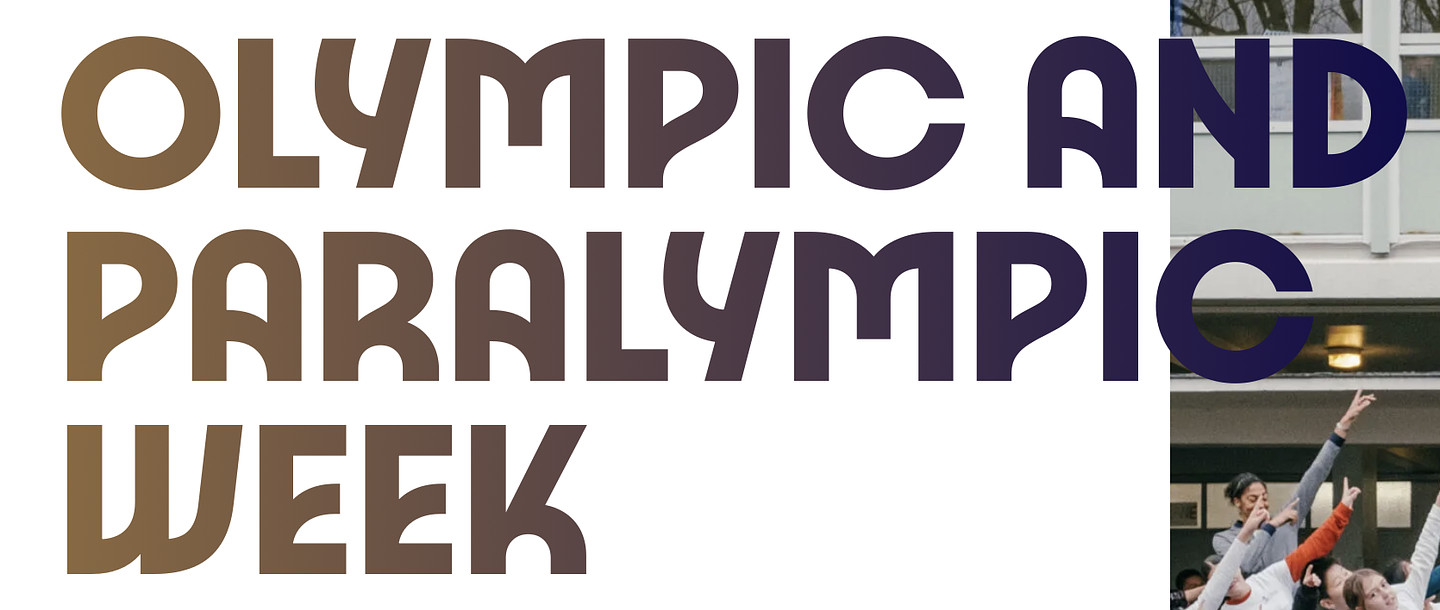
Paris 2024 Olympics
2024 파리 올림픽, 패럴림픽 공식 폰트로 굵기별로 따로 있지 않고 한 폰트 파일안에 프로그램에서 주는 크기에 따라 자동으로 7가지 굵기가 변하는 가변 글꼴(Variable) 입니다. 거기에 기울기(italic) 까지 주면 총 14가지 변화가 가능한 글꼴입니다. Julie Soudanne, Elliott Amblard, Tina Payet, Sylvain Boyer가 합작하여 디자인 하였고, Sylvain Boyer가 운영하는 ecobranding-design 이라는 회사에서 제조하였습니다. 2024 파리 올림픽이 환경을 생각하는 올림픽인 만큼 이 폰트를 제조한 ecobranding-design 이란 회사도 디자인에 있어 환경을 생각하는 디자인을 하고 있습니다. 이 회사의 웹사이트 https://ecobranding-design.com/ 에 가보면 잉크를 적게 먹는 색깔 조합 같은 독특한 자료들이 있네요^^ 현재 아래 사이트에서 다운로드 가능하구요, 가변 폰트라서 이름을 Paris 2024 Variable 이라고 올려놨지만, 정식 명칭은 Paris 2024 Olympics 가 맞습니다. 다운로드 사이트https://wisabo.com/item/1/paris-2024-variable/